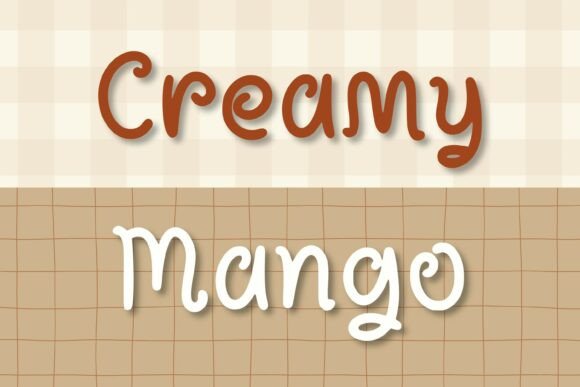
Creamy Mango
適切なデザイン要素を見つけるのは難しい場合がありますが、Creamy Mangoは作品を即座に引き立てる優れたコレクションを提供します。
POD(オンデマンド印刷)製品、結婚式の招待状、またはソーシャルメディアのグラフィックを作成している場合でも、Creamy Mangoは理想的です。